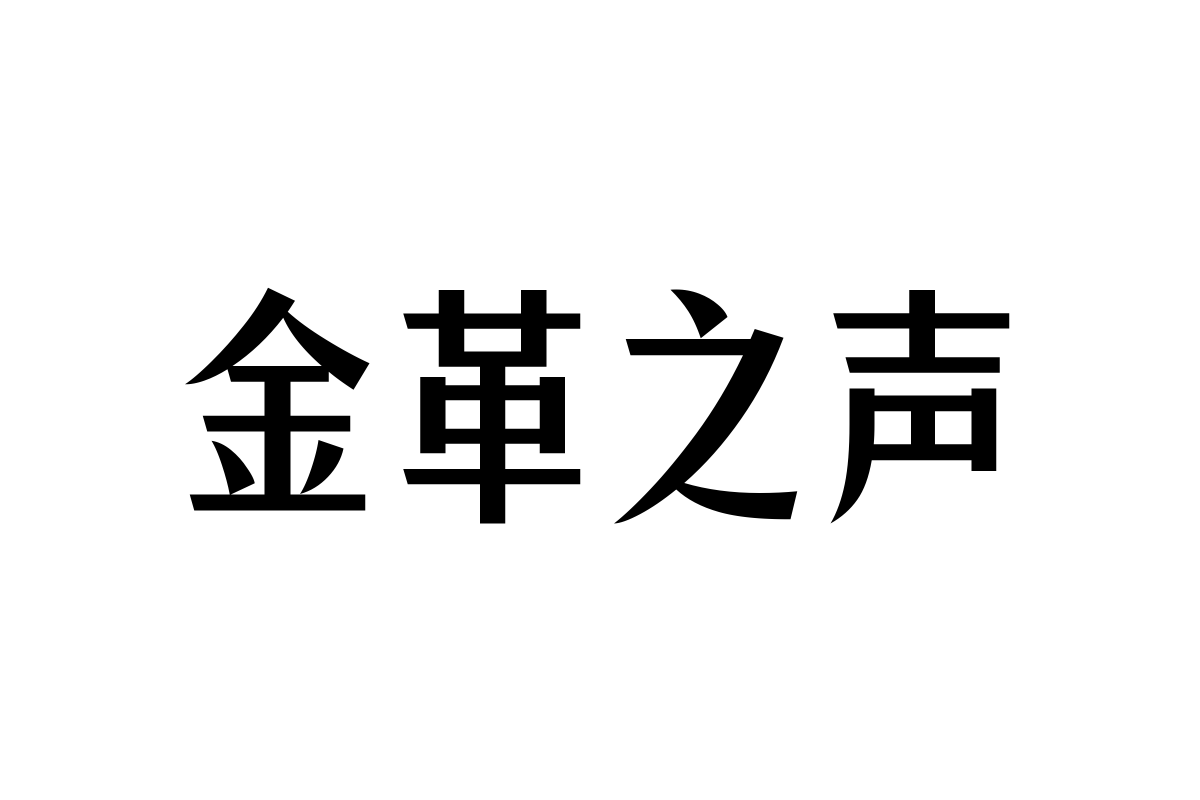
三极锐宋黑简体粗体是一套具有现代感和实用性的字体。它由三个不同的粗细版本组成,分别是细体、中体和粗体,以满足不同需求的用户。
1. 细体:适用于需要清晰易读的文本,如标题或正文。它的线条细腻,字形紧凑,易于阅读。
2. 中体:适用于需要中等清晰度的文本,如广告牌或菜单。它的线条适中,字形饱满,能够吸引观众的注意力。
3. 粗体:适用于需要强调的文本,如强调重点或标题。它的线条粗壮,字形饱满,能够突出重要信息。
三极锐宋黑简体粗体的特点在于其简洁明了的线条和清晰的字形,使其在各种场景下都能发挥出色的效果。无论是用于印刷、电子屏幕还是其他媒介,它都能提供良好的视觉体验。